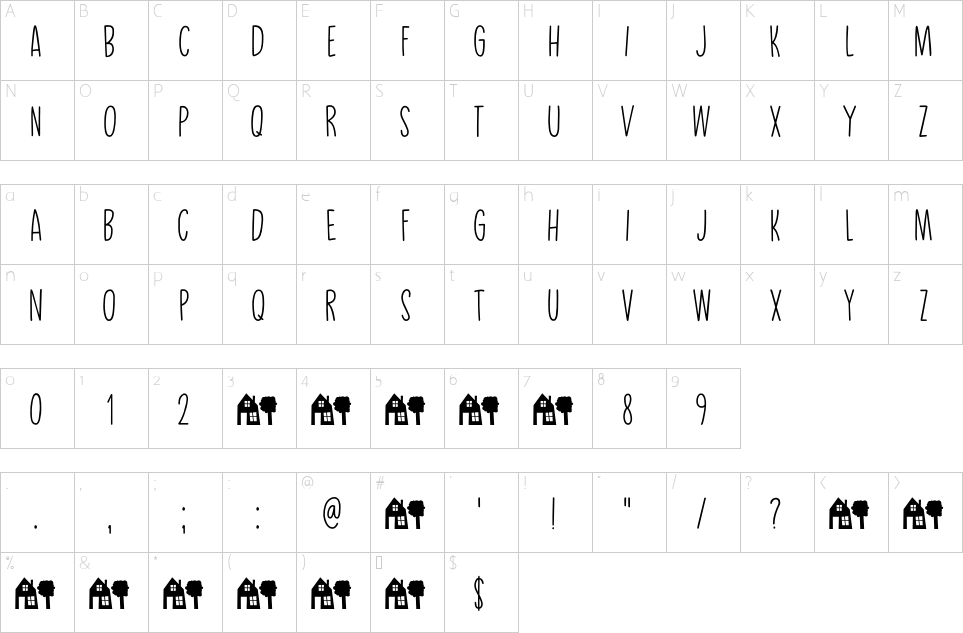
Descubra a Daily Challenge Font, uma fonte grátis perfeita para adicionar um toque único a seus projetos digitais. Desenvolvida por Hanoded, esta font tem sido descarregada 86 vezes e é ideal para quem procura estilos únicos e versáteis sem precisar gastar dinheiro. Perfumada com traços elegantes e linhas sutilmente distintas, a Daily Challenge Font oferece uma variedade de opções que certamente vão agradar os criadores digitais. Seja para textos legíveis ou gráficos coloridos, esta font destaca-se por seu design limpo e equilibrado. Se você está procurando por uma opção de fonte gratuita que ainda respeita sua criatividade e estilo, Daily Challenge Font é a escolha perfeita. Download já e experimente a versatilidade desta font no seu próximo projeto!